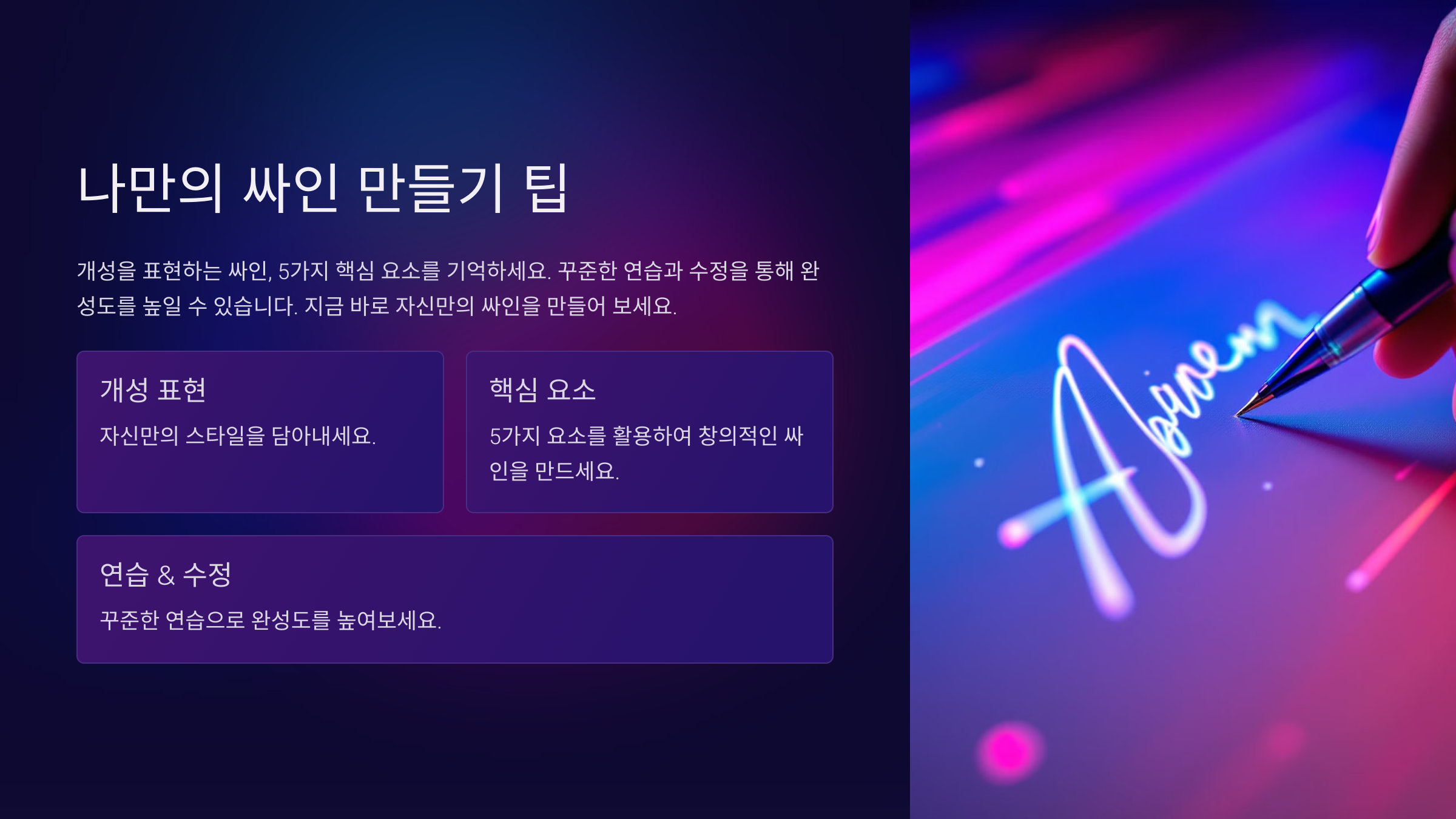
싸인은 작은 변화만으로도 완전히 다른 느낌을 줄 수 있는 강력한 디자인 요소예요. 이니셜 하나, 획의 굵기, 곡선의 흐름 등 작은 차이가 싸인의 분위기를 완전히 바꿀 수 있어요. ✍🔥
내가 생각했을 때, 싸인의 작은 변화가 주는 효과를 알고 있다면 더 멋지고 독창적인 스타일을 만들 수 있을 거예요. 이제 싸인의 세부 요소를 조절하면서 스타일 변화를 직접 확인해볼까요? 🚀
싸인의 작은 변화가 큰 차이를 만든다 🔍
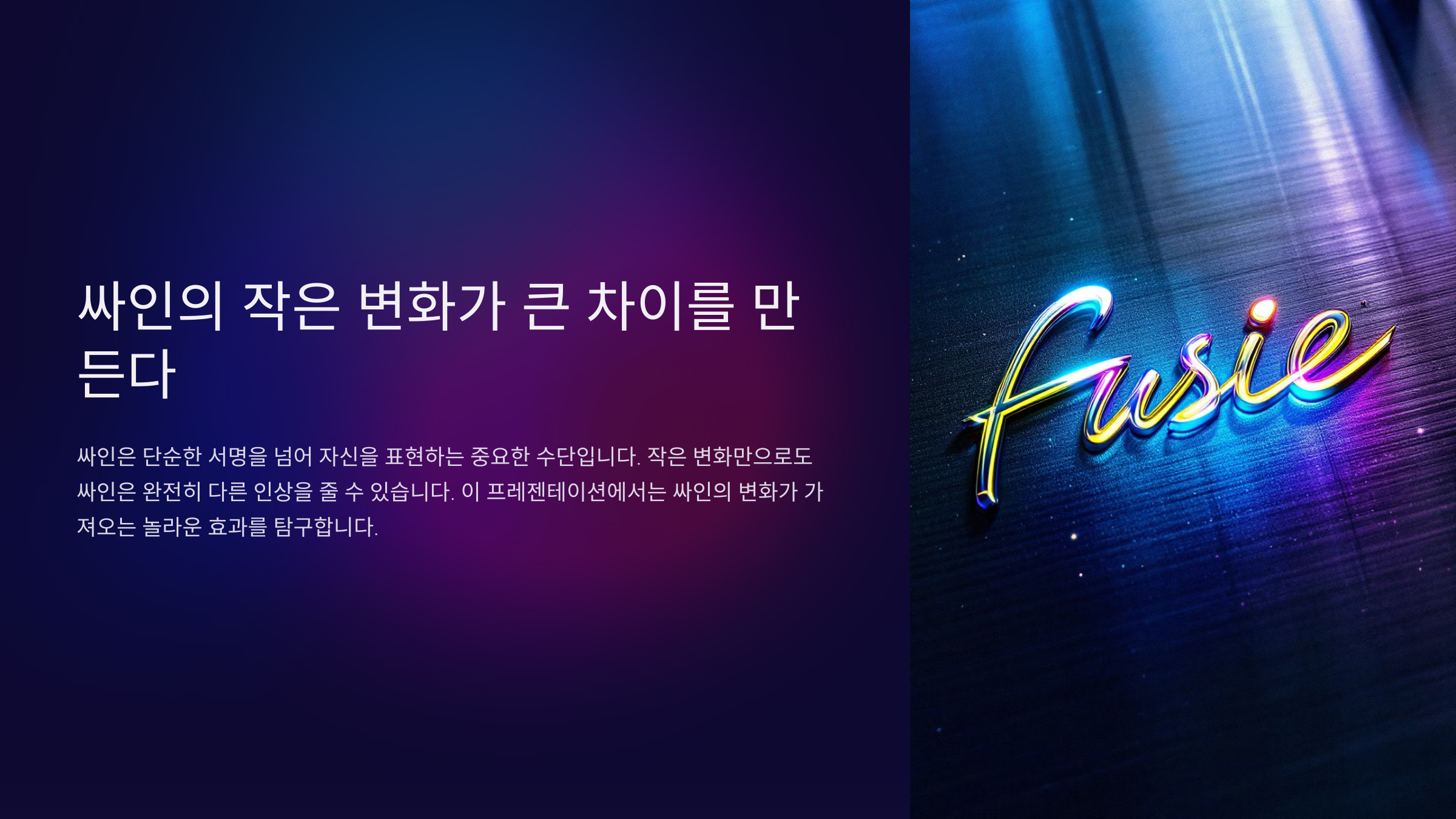
싸인은 단순한 글자가 아니라 나만의 개성을 담은 디자인 요소예요. 작은 변화 하나만 줘도 완전히 다른 느낌의 싸인을 만들 수 있답니다. ✍🔥
🔹 싸인의 미묘한 차이가 주는 효과
✔ 이니셜 하나만 바꿔도 분위기가 달라짐
✔ 획의 길이와 굵기만 조절해도 스타일이 달라짐
✔ 곡선과 직선 조합에 따라 싸인의 느낌이 확 달라짐
✔ 작은 기호(⭐, ✔, •)를 추가하면 개성이 강조됨
📌 싸인의 작은 차이가 주는 효과 ✨
변화 요소 스타일 변화 효과 이니셜 변경 이름의 첫 글자를 강조하거나 변형 더 강렬하고 기억에 남는 스타일 획 굵기 조절 굵은 획 또는 얇은 획 활용 단단한 느낌 vs 우아한 느낌 연출 곡선과 직선 변화 부드러운 곡선 또는 강한 직선 활용 유려한 느낌 vs 강렬한 느낌 연출 기호 추가 별⭐, 밑줄━, 점• 추가 개성과 차별화된 스타일 강조 이제 이니셜 하나만 바꿔도 싸인의 느낌이 달라지는 이유를 살펴볼까요? 🔠
이니셜 하나만 바꿔도 싸인의 느낌이 달라지는 이유 🔠
이니셜(이름의 첫 글자)은 싸인의 핵심 포인트예요. 이니셜을 조금만 바꿔도 싸인의 분위기나 스타일이 완전히 달라질 수 있어요. ✍🔥
🔹 이니셜 변화가 주는 스타일 차이
✔ 대문자로 강렬한 느낌 만들기 – 힘 있고 단단한 인상
✔ 소문자로 부드러운 스타일 연출 – 유려하고 감각적인 디자인
✔ 이니셜을 기울여서 독특한 포인트 주기 – 개성적인 느낌 강조
✔ 이니셜 크기를 키워 시그니처 스타일 완성 – 브랜드 같은 싸인 효과
📌 이니셜 하나의 변화로 달라지는 싸인 스타일 ✨
이니셜 스타일 싸인의 변화 느낌 대문자 (ex. J.K.) 이니셜을 대문자로 강조 힘 있고 강한 인상 소문자 (ex. j.k.) 이니셜을 부드럽게 소문자로 사용 감각적이고 부드러운 느낌 기울임 (ex. J.K.) 이니셜을 기울여서 독특한 스타일 유니크하고 개성 강한 스타일 이니셜 크기 강조 (ex. J.K. Smith) 이니셜을 크게 만들고 나머지 글자는 작게 시그니처 느낌의 브랜드화된 싸인 이제 획의 방향과 굵기 변화로 싸인의 스타일을 차별화하는 방법을 살펴볼까요? 🎨
획의 방향과 굵기 변화로 스타일 차별화 🎨
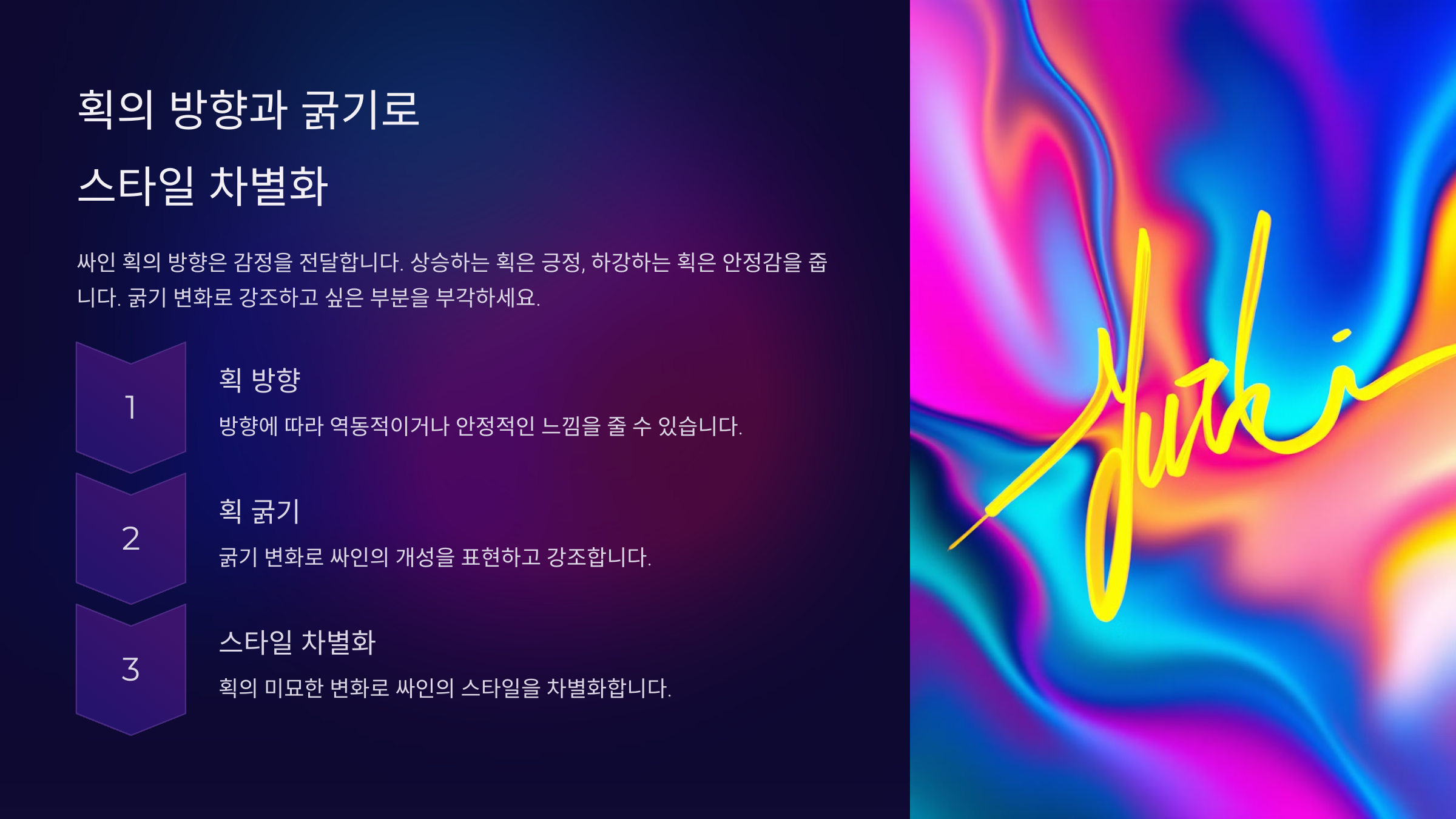
싸인의 획을 조절하는 것만으로도 완전히 새로운 느낌을 줄 수 있어요. 획을 짧게, 길게, 굵게, 얇게 조정하면 싸인의 개성이 한층 더 살아납니다! ✍🔥
🔹 획의 방향과 굵기 변화가 주는 효과
✔ 수평선을 강조하면 안정적인 느낌 – 균형 잡힌 디자인
✔ 세로 획을 강조하면 강렬한 느낌 – 단단하고 강한 인상
✔ 굵은 획을 사용하면 힘 있는 싸인 – 확실한 존재감 연출
✔ 얇은 획을 활용하면 우아한 싸인 – 부드럽고 감각적인 스타일
📌 획 조절에 따른 싸인 스타일 변화 ✨
획 스타일 싸인의 느낌 추천 대상 수평선 강조 차분하고 균형 잡힌 스타일 공식 문서나 계약서 서명 세로 획 강조 강렬하고 파워풀한 느낌 연예인, 아티스트, 사업가 굵은 획 사용 강한 존재감과 확실한 인상 대중적인 영향력을 원하는 사람 얇은 획 활용 우아하고 감성적인 스타일 디자이너, 작가, 예술가 이제 곡선과 직선 조합으로 싸인의 개성을 살리는 방법을 살펴볼까요? ✅
곡선과 직선 조합으로 싸인 개성 살리기 ✅
곡선과 직선을 어떻게 배치하느냐에 따라 싸인의 개성이 극명하게 달라져요. 부드러운 느낌을 원하면 곡선을, 강렬한 느낌을 원하면 직선을 강조하면 돼요! ✍🔥
🔹 곡선 vs 직선 싸인 스타일 차이
✔ 곡선 위주 싸인 – 유연하고 부드러운 스타일, 감성적인 분위기
✔ 직선 위주 싸인 – 정돈된 느낌, 단단하고 강한 인상
✔ 곡선 + 직선 조합 – 균형 잡힌 디자인, 모던하고 세련된 스타일
✔ 획의 연결을 활용 – 자연스럽게 이어지는 흐름으로 세련된 느낌 연출
📌 곡선과 직선 활용법 ✨
싸인 스타일 특징 추천 대상 곡선 위주 부드럽고 우아한 느낌, 감성적인 분위기 예술가, 작가, 크리에이터 직선 위주 정돈되고 힘 있는 스타일, 강한 인상 CEO, 사업가, 법조인 곡선 + 직선 조합 균형 잡힌 디자인, 현대적이고 세련된 느낌 디자이너, 마케터, 연예인 획의 연결 활용 부드럽게 이어지는 흐름, 자연스럽고 세련된 스타일 모든 분야 활용 가능 이제 한 글자 추가 혹은 삭제가 주는 효과를 알아볼까요? ✂
한 글자 추가 혹은 삭제의 효과 ✂
싸인에서 한 글자만 추가하거나 삭제해도 전체적인 분위기가 달라질 수 있어요. 특히 성이나 이니셜을 생략하거나 강조하는 방식에 따라 전혀 다른 스타일의 싸인이 완성될 수 있답니다! ✍🔥
🔹 한 글자 추가/삭제의 효과
✔ 성(姓) 삭제 → 빠르고 심플한 느낌
✔ 이니셜 추가 → 브랜드 같은 강렬한 인상
✔ 이름 줄이기 → 부드럽고 간결한 스타일
✔ 밑줄 추가 → 개성 있고 스타일리시한 디자인
📌 싸인에서 한 글자 변화가 주는 차이 ✨
변경 방법 싸인의 변화 느낌 성(姓) 삭제 이름만 남겨서 짧고 간결하게 빠르고 심플한 느낌 이니셜 추가 이니셜을 추가하여 시그니처 느낌 강조 강렬하고 브랜드 같은 인상 이름 줄이기 이름을 약어로 줄여 빠르게 작성 가능 부드럽고 세련된 스타일 밑줄 추가 싸인의 마무리에 밑줄을 넣어 강조 스타일리시하고 개성적인 디자인 이제 유명인의 싸인 변화 사례를 분석해볼까요? 🏆
유명인의 싸인 변화 사례 분석 🏆
유명인들의 싸인은 단순한 서명이 아니라 자신을 대표하는 브랜드 요소예요. 시간이 지나면서 스타일이 변하거나 더 세련되고 간결한 형태로 발전하는 경우가 많아요. ✍🔥
🔹 유명인의 싸인 변화 패턴
✔ 처음에는 정교한 필기체 → 이후에는 간결한 스타일로 변화
✔ 이니셜만 남기거나 강렬한 기호를 추가
✔ 싸인의 크기가 작아지고 속도가 빨라짐
✔ 자연스럽고 부드러운 흐름을 강조하는 방향으로 발전
📌 유명인의 싸인 스타일 변화 ✨
유명인 초기 스타일 현재 스타일 변화 포인트 마이클 조던 필기체 스타일 이니셜 'MJ'로 단순화 빠른 서명 가능 스티브 잡스 흘려 쓴 필기체 이름 일부만 남긴 초간결 스타일 미니멀리즘 강조 테일러 스위프트 곡선이 많은 싸인 심플한 'TS' 이니셜로 변경 짧고 세련된 인상 일론 머스크 복잡한 서명 초간결한 이니셜 'EM' 빠른 서명과 강렬한 인상 이제 싸인에 대한 궁금증을 해결할 시간! FAQ에서 자주 묻는 질문을 정리해볼까요? ❓
FAQ ❓
Q1. 싸인을 만들 때 가장 중요한 요소는 무엇인가요?
A1. 싸인을 만들 때 가장 중요한 요소는 간결함과 개성이에요. ✔ 너무 복잡하지 않으면서도 빠르게 쓸 수 있어야 함 ✔ 이름의 특징을 살려 자신만의 스타일을 반영하는 것 ✔ 가독성이 좋고, 기억에 남는 디자인이 중요함
Q2. 싸인을 계속 바꿔도 되나요?
A2. 개인적인 싸인은 자유롭게 바꿀 수 있지만, 공식 문서에서 사용하는 싸인은 신중해야 해요. ✔ 은행, 공공기관 등의 서류에 등록된 싸인은 일관성을 유지하는 것이 좋음 ✔ 새로운 싸인을 정착시키려면 충분한 연습이 필요함
Q3. 싸인에 기호(⭐, ✔, •)를 추가해도 괜찮을까요?
A3. 기호를 활용하면 싸인의 개성을 더욱 살릴 수 있어요. ✔ 별(⭐), 점(•), 밑줄(━) 등으로 포인트 추가 가능 ✔ 너무 많은 장식은 가독성을 떨어뜨릴 수 있으므로 적절하게 사용하기
Q4. 유명인의 싸인을 따라 하면 문제가 될까요?
A4. 유명인의 싸인을 참고하는 것은 괜찮지만, 완전히 동일하게 따라 하는 것은 권장되지 않아요. ✔ 유명인의 스타일을 참고해 나만의 변형을 가미하는 것이 중요 ✔ 자신만의 개성이 담긴 싸인을 만드는 것이 더 좋은 방법
Q5. 싸인의 크기는 어떻게 조절해야 할까요?
A5. 싸인의 크기는 사용 환경에 따라 조절하는 것이 좋아요. ✔ 공식 문서에서는 작은 크기로 깔끔하게 ✔ 팬 사인회, 명판에서는 크고 인상적으로 작성
Q6. 싸인을 더 빠르게 쓰는 방법이 있나요?
A6. 싸인을 빠르게 쓰려면 불필요한 요소를 제거하고 자연스러운 흐름을 익히는 것이 중요해요. ✔ 이니셜을 활용해 간결한 디자인 만들기 ✔ 획을 줄이고 자연스럽게 이어지는 흐름으로 연습하기 ✔ 하루 5~10분씩 반복 연습하여 손에 익히기
Q7. 싸인을 한글과 영어 중 어떤 걸로 만드는 것이 좋을까요?
A7. 한글과 영어 중 어떤 걸 사용할지는 본인의 스타일과 용도에 따라 선택하면 돼요. ✔ 한글 싸인 – 독창적이고 한국적인 느낌 강조 ✔ 영어 싸인 – 글로벌하게 활용 가능하고 세련된 느낌 ✔ 한글+영어 조합 – 성(姓)은 한글, 이름은 영어 등 독특한 스타일 가능
Q8. 싸인을 디지털 문서에서 사용할 때 주의할 점이 있나요?
A8. 디지털 문서에서 싸인을 사용할 때는 일관성을 유지하는 것이 중요해요. ✔ 태블릿, 스타일러스 펜을 활용해 자연스럽게 연습 ✔ PNG 파일로 저장하여 투명 배경으로 문서에 삽입 가능 ✔ Adobe Sign, DocuSign 같은 전자 서명 도구 활용
이제 싸인의 작은 변화가 얼마나 큰 차이를 만드는지 완벽하게 이해했어요! 🎯 연습을 통해 자신만의 독창적인 싸인을 완성하고, 공식 문서에서도 활용해 보세요! ✍🔥